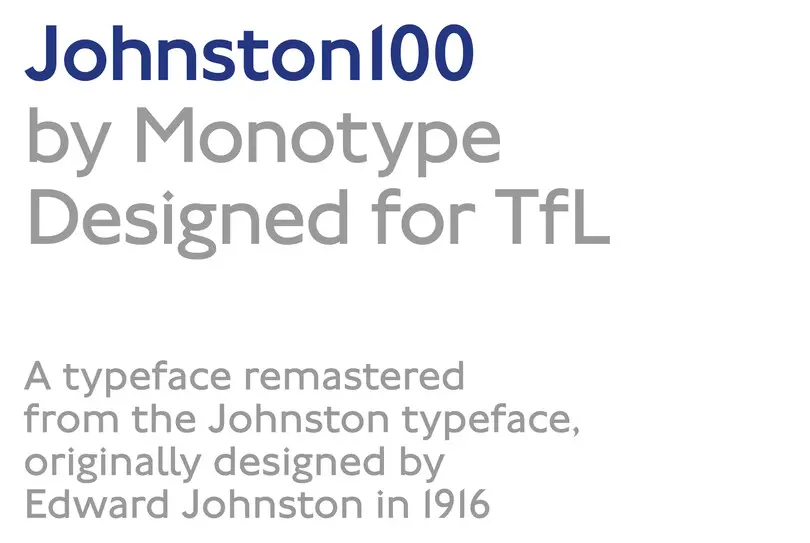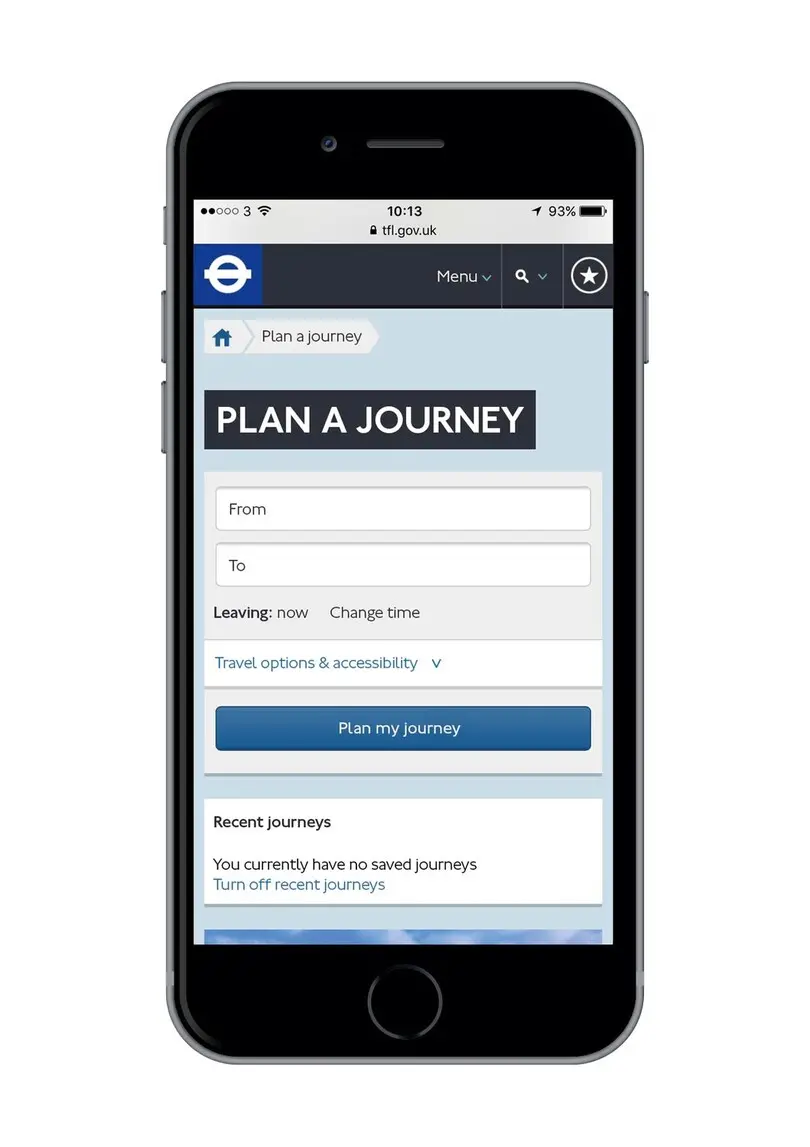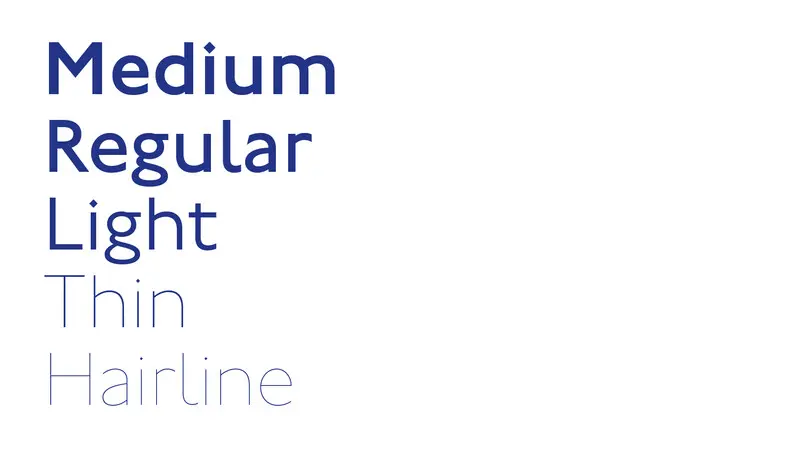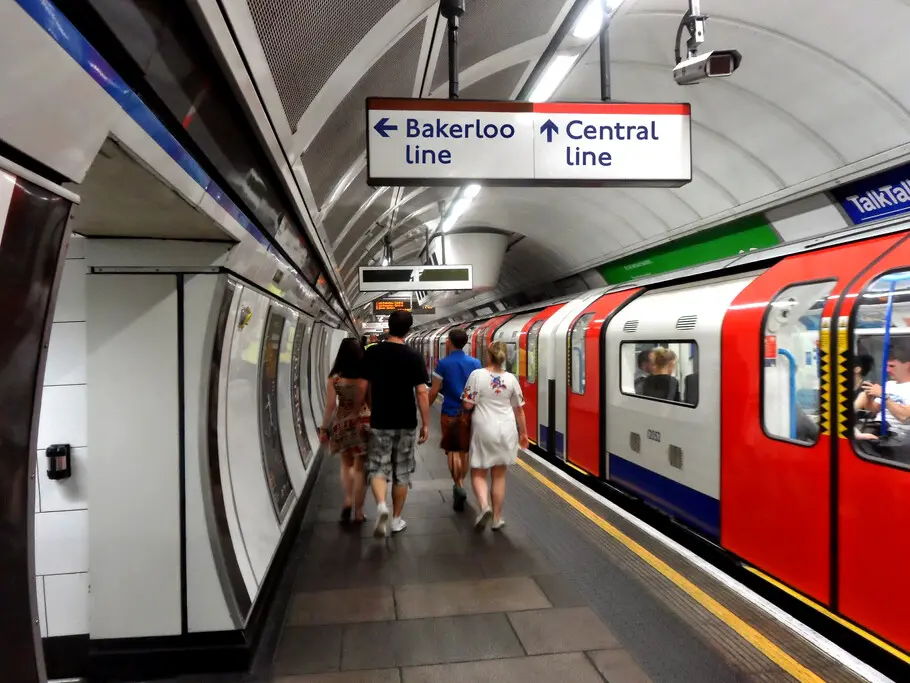
Aidez vos clients à s’orienter grâce à la bonne police de caractères.
“ D’après une étude récente menée par le Nielsen/Norman Group, au cours d’une visite ordinaire sur une page Web standard, un utilisateur a le temps de lire tout au plus 28 % des mots affichés et il a plutôt tendance à en lire 20 %. ”
Imaginez-vous dans une station de métro grouillante de monde en train de fendre la foule pour monter dans la prochaine rame. Vous cherchez des yeux des panneaux qui vous indiquent la bonne direction. Une fraction de seconde pour les lire et vous vous élancez jusqu’à votre quai.
Le texte de ces panneaux doit être lisible et clair et sa taille adaptée à leur emplacement ainsi qu’à l’importance du message, de sorte que vous n’ayez pas à vous arrêter pour chercher les informations dont vous avez besoin. En effet, on vous attend pour dîner et quelques secondes perdues pourraient suffire à transformer le quart d’heure de politesse en un retard pour le moins inconvenant.
Un site web fonctionne sensiblement de la même façon, si ce n’est qu’il présente moins de risques de rendez-vous manqués. Mais l’interaction entre l’internaute et le contenu du site est presque tout aussi immédiate. Sur un site web comme dans une station de métro (ou un aéroport, pour prendre un autre exemple), un texte bien pensé peut éviter de nombreuses déconvenues et créer une expérience utilisateur positive.
Des contenus survolés en un clin d’œil.
D’après une étude récente menée par le Nielsen/Norman Group, « au cours d’une visite ordinaire sur une page Web standard, un utilisateur a le temps de lire tout au plus 28 % des mots affichés et il a plutôt tendance à en lire 20 %. » Ce chiffre varie quelque peu en fonction du volume de texte sur la page. Mais ces statistiques font ressortir une vérité première, surtout si on se souvient que la plupart des gens passent 15 secondes sur une page Web en moyenne : ce n’est pas pour lire que la plupart de vos visiteurs viennent sur votre site.
Ils viennent plutôt pour y trouver des informations. Autrement dit, un site web, en règle générale, est un outil que l’on utilise, d’où l’emploi du terme « utilisateur ». Au fond, la plupart des sites web sont conçus de manière à faciliter l’accomplissement de tâches simples : faire des achats, gérer ses opérations bancaires, planifier ses voyages – même si on trouve également des publications numériques et d’autres sites nécessitant un investissement de plus longue durée.
Coût minimal d'interaction.
« Les gens ne lisent pas de gauche à droite ni de la première à la dernière ligne » affirme Theresa Mershon, directrice de la création spécialisée dans le design de l’expérience utilisateur et dans la conception des produits chez Hearst Magazines Digital Media (HMDM). « Quand une personne atterrit sur un site, elle prend la température en lisant le titre et la première phrase. Puis elle fait défiler l’article et le survole en jetant un œil aux images et au titre des paragraphes — tout ce qui n’appartient pas au corps du texte — avant de décider si cela vaut la peine de s’investir dans la lecture du corps du texte. »
Cette pratique est connue sous le nom de « coût minimal d’interaction ». L’expression désigne l’effort minimal requis pour déterminer si un contenu vaut la peine d’être lu. Il y a fort à parier que vous avez vous-même procédé ainsi, comme la plupart des lecteurs de cet article, avant de décider de poursuivre votre lecture.
“ Les gens ne lisent pas de gauche à droite ni de la première à la dernière ligne. ”
Theresa Mershon, directrice de la création spécialisée chez Hearst Magazines Digital Media (HMDM).
« Les utilisateurs savent très bien filtrer le contenu d’une page pour ne garder que ce qu’ils jugent important, » explique Theresa Mershon. « Ils sont habitués à se battre pour obtenir ce qu’ils veulent. » En effet, les consommateurs s’attendent aujourd’hui à devoir effectuer un parcours du combattant lorsqu’ils visitent une page Internet. Ils doivent écarter les annonces publicitaires intempestives et autres pop-ups qui nuisent à la fluidité de leur visite. Sans compter que, bien souvent, ils surfent alors même qu’ils sont exposés à une foule de distractions extérieures.
« Personne ne peut prétendre capter entièrement l’attention de l’utilisateur », fait remarquer Theresa Mershon. « Outre le Web lui-même, outre les 20 autres onglets que l’utilisateur a ouverts, il y a tout ce qui se passe hors écran, dans le monde réel. Alors, comment fait-on pour être perçu comme une aide et pas comme une distraction ? Comme quelqu’un qui ne cherche pas à entourlouper l’utilisateur mais à lui fournir exactement ce qu’il cherche ? »
Il faut bien comprendre qu’on ne sait pas toujours dans quelles circonstances, à quel moment ou depuis quel endroit un utilisateur accède à un site. Repensez à toutes les fois où une situation étrange, inattendue ou stressante est venue entraver votre quête d’informations en ligne. Demandez-vous combien de fois vous vous êtes dit (ou vous avez même crié) : « Mais pourquoi ça ne marche pas, bon sang ?! »
Heureusement, vous pouvez faire une utilisation intelligente des polices de caractère. Une telle stratégie contribue largement à dissiper cette frustration.
En d’autres termes : faites simple. N’oubliez pas que l’attention de votre utilisateur ne vous est garantie qu’une poignée de secondes. Alors, faites en sorte que ces secondes comptent, pour votre utilisateur comme pour vous. Grâce à une stratégie typographique bien pensée, vous pouvez faire en sorte que les visites sur votre site se déroulent sans accroc et que vos internautes en gardent un (bon) souvenir… C’est ainsi que vous fidéliserez votre clientèle.